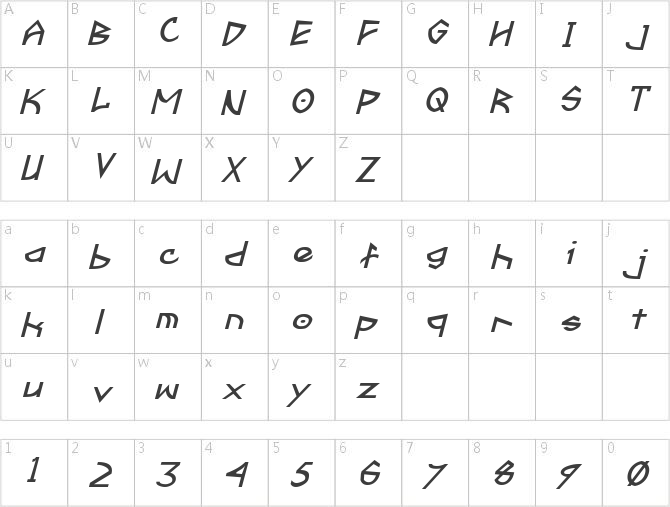
Fractyl Bold Italic 詳情頁
Fractyl Bold Italic字體字庫是一款讓人賞心悅目、百看不厭的英文字體,適合各類廣告和產(chǎn)品包裝設(shè)計應(yīng)用,字體大小0.03MB,格式為ttf字體,上傳用戶是 造物設(shè)計師,作者/版權(quán)方為未知